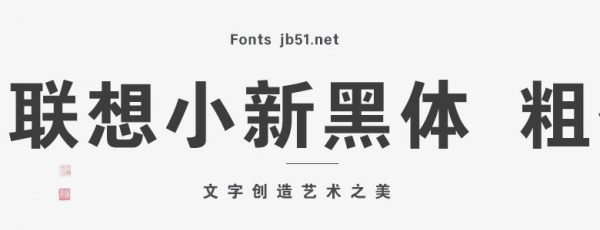
基于聯(lián)想小新“輕薄化”“高能化”的特點(diǎn),以此為創(chuàng)作理念,以簡(jiǎn)約的筆畫(huà)、精簡(jiǎn)的線條、柔和的弧度,打造出一款人文與科技交織的黑體字。
平直極簡(jiǎn)的橫豎筆畫(huà),突顯品牌的科技感、未來(lái)感。常規(guī)體中筆畫(huà)粗細(xì)的微弱差距,營(yíng)造良好的視覺(jué)穩(wěn)定性。
為深度匹配品牌需求,聯(lián)想小新黑體提供常規(guī)、粗體2款字重,同時(shí)在6763漢字基礎(chǔ)上,增加400個(gè)常用漢字,可滿足正文、說(shuō)明文、標(biāo)題等多種場(chǎng)景的應(yīng)用需求。
聯(lián)想小新黑體常規(guī)體
字面框與字身框占比82%左右,大段排版時(shí)增加閱讀舒適性。相對(duì)縮小的字宮,帶來(lái)更多的視覺(jué)關(guān)注力。
聯(lián)想小新黑體粗體
字面框與字身框占比85%左右,重點(diǎn)信息、標(biāo)題使用時(shí)醒目易讀;相對(duì)稍微內(nèi)收的字宮,提升了人文感。
聯(lián)想小新黑體常規(guī)體|字母數(shù)字與漢字的基本高度比例在82%左右,在進(jìn)行漢字與字母數(shù)字混排時(shí),閱讀舒適性更高。
聯(lián)想小新黑體粗體|字母數(shù)字與漢字的基本高度比例在80%左右,在混排時(shí),字母數(shù)字與漢字高度對(duì)比明顯,增加對(duì)字母數(shù)字的注意力,提升分辨關(guān)鍵信息的速度。